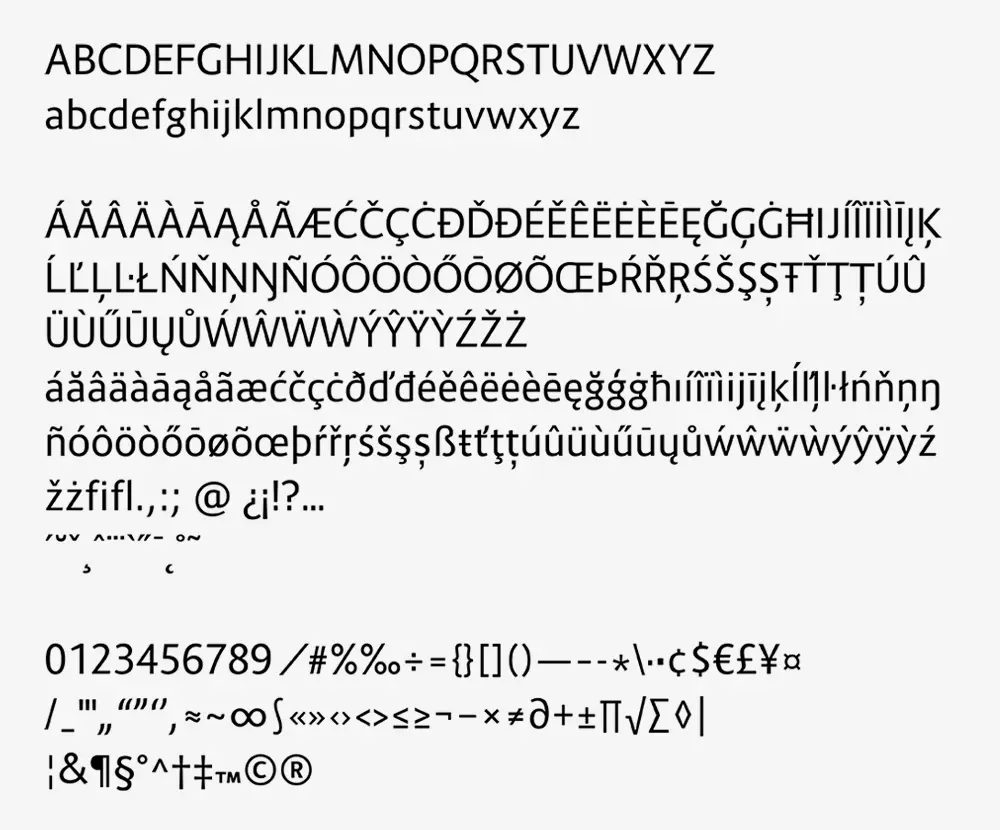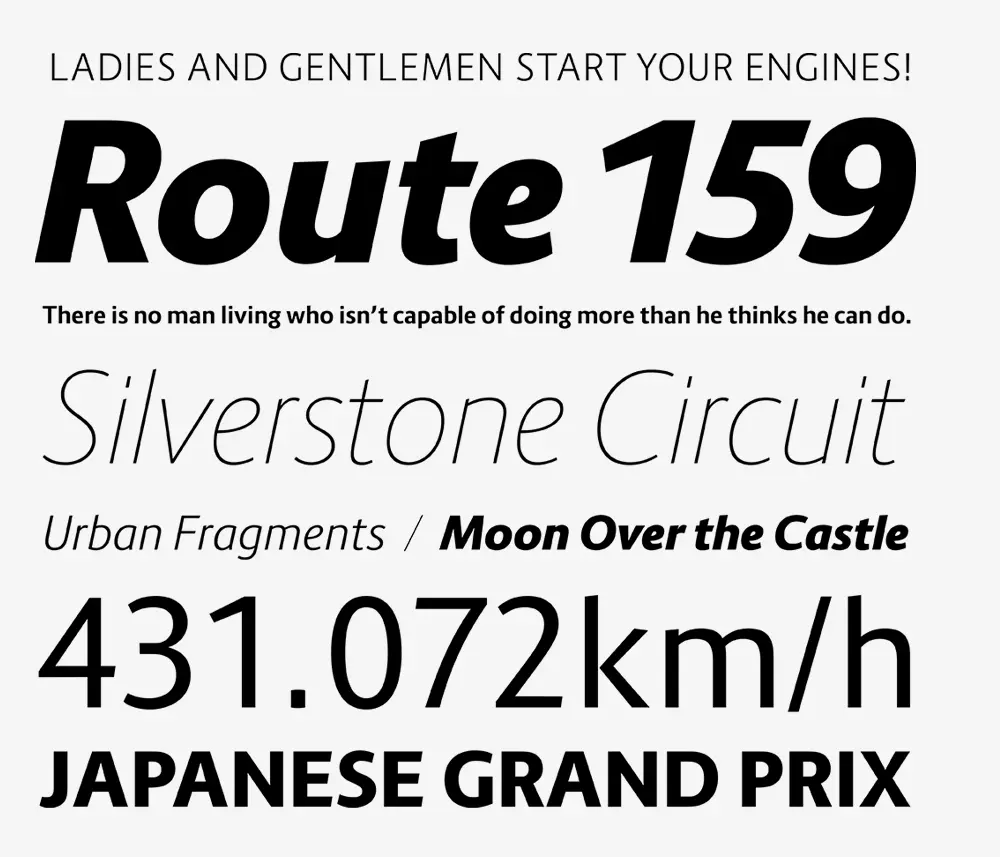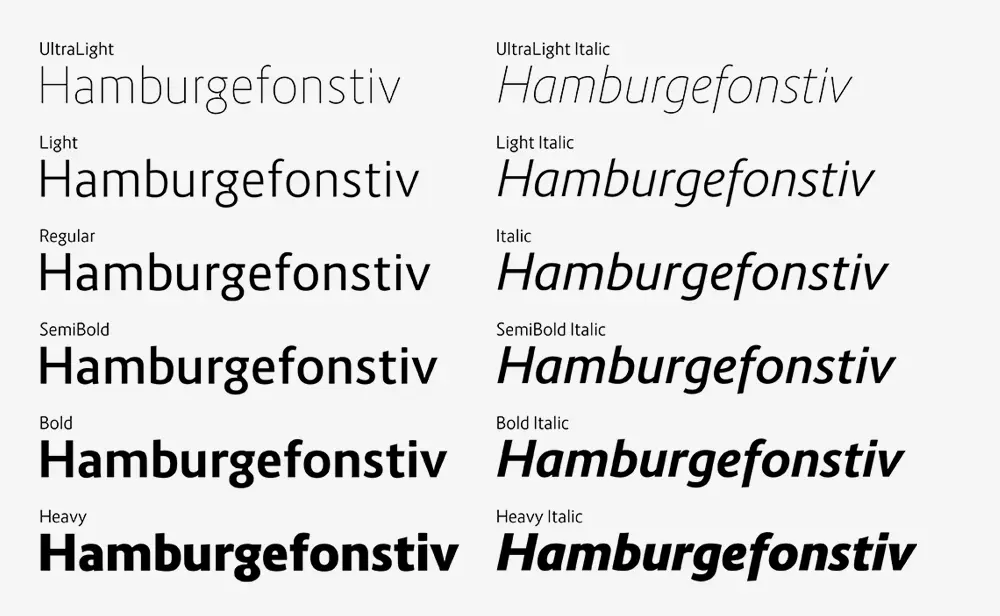
Route 159預覽
Route 159介紹
Route 159 是一種新開發的無襯線字體,作為點冒號的網絡字體。憑藉我們之前發佈的 Vegur 和 Aileron 的開發經驗,我們更加註重屏幕的可視性和可讀性。字母內部的對應部分,包括小寫字母 b、d、p 和 q,設計得更寬,即使是小尺寸也很難被壓碎。
Route 159は、ドットコロン用のWebフォントとして新たに開発したサンセリフフォントです。先に公開したVegurやAileronを製作した経験を生かしより畫面上での視認性や可読性を重視しました。小文字のb, d, p, qをはじめとして文字の內側のカウンター部分を広くとれるデザインにし、小サイズでも潰れにくくしています